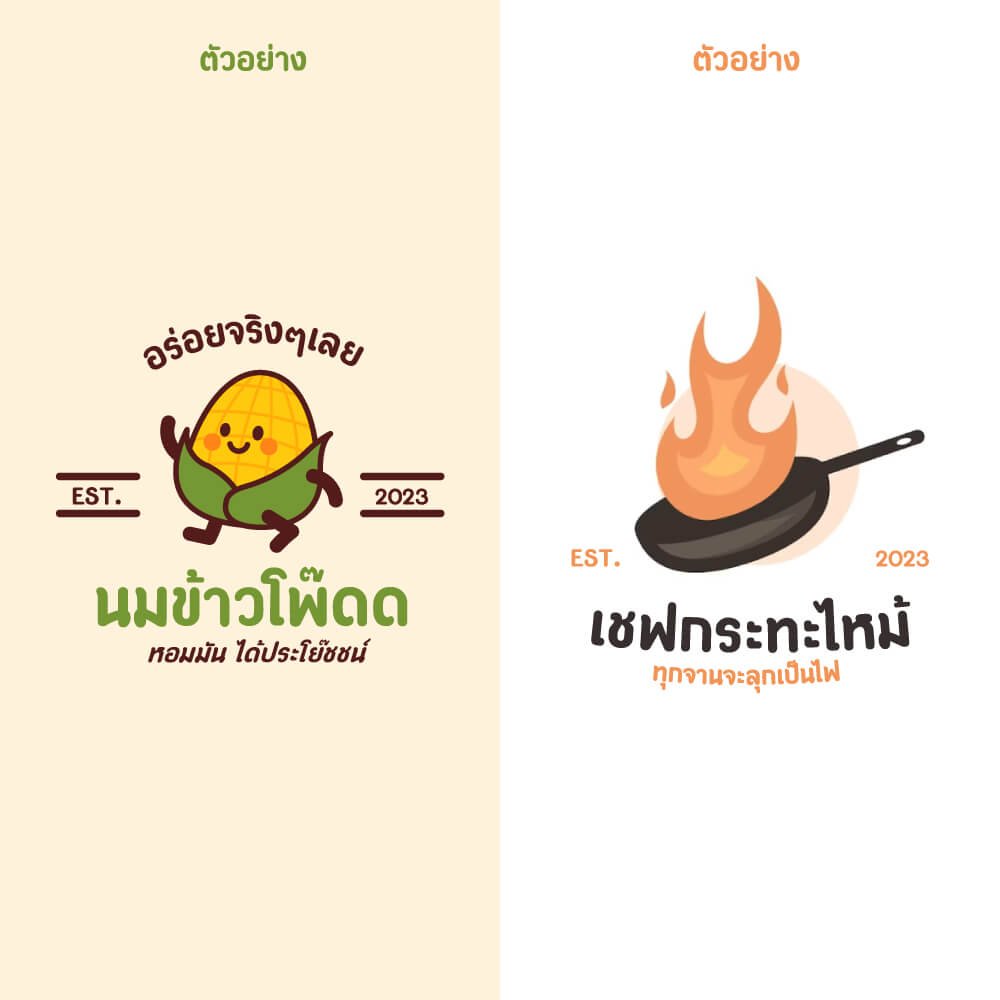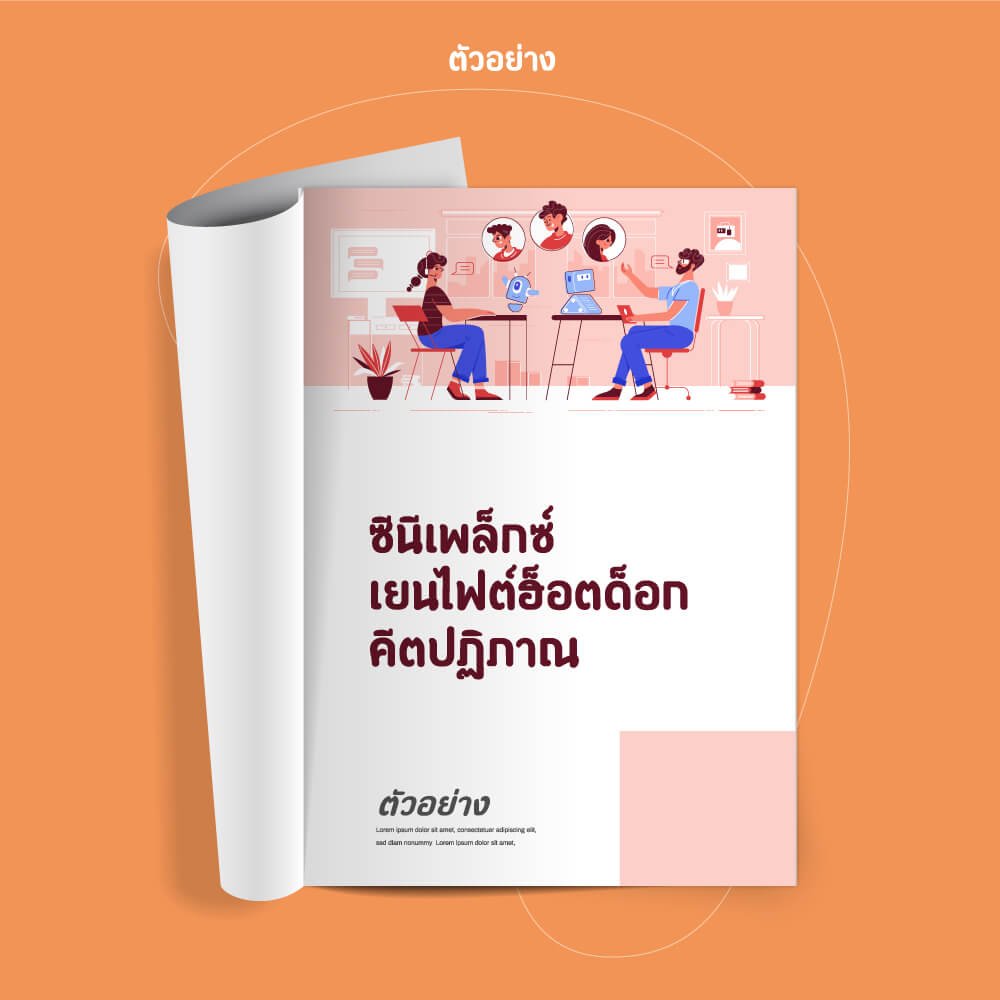
เจนจรัส แสงมน (Jenjrus Saengmon)
ฟอนต์เจนจรัส แสงมน เป็นฟอนต์ตัวหนามนๆ อ่านง่าย ใช้ได้ทั้งฟิลลิ่งสนุก เรียบร้อย เหมาะกับเป็นหัวข้อหรือทำป้ายต่างๆ
ฟอนต์นี้เป็นผลงาน ชุดที่ 6 ของคุณพ่อ อายุ 77 ปีแล้ว ที่รักการออกแบบฟอนต์เป็นงานอดิเรกครับ